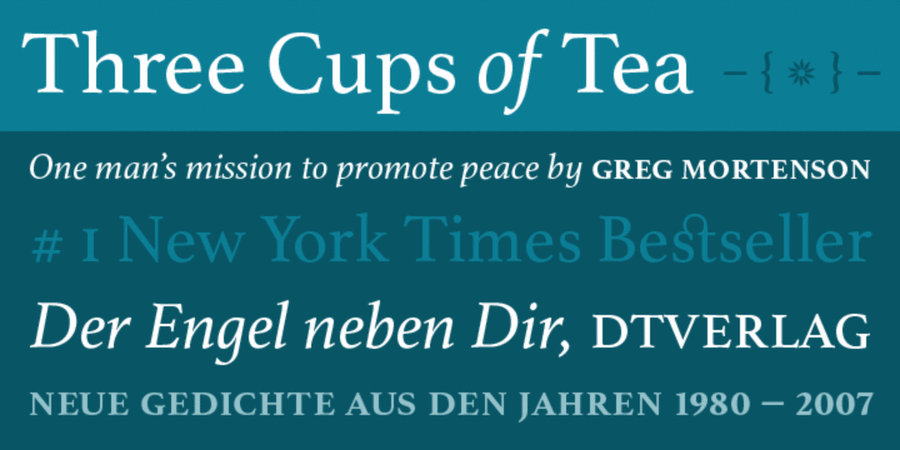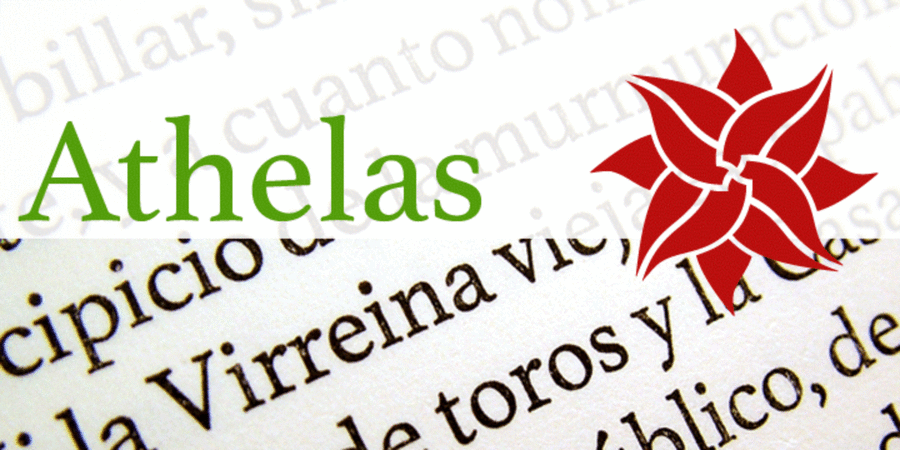
Це спроба повернутися до високого мистецтва друкарства, натхненна класиками британської літератури. Ателас нагороджений на шрифтовому конкурсі Granshan 2008. Цей шрифт в повній мірі використовує друкарську тишу, порожній простір на полях, між стовпцями, рядками, словами, формами літер і, нарешті, всередині самих символів. Він також призначений для використання переваг технічних досягнень офсетного друку. Ателас демонструє свої найкращі сторони в ретельно продуманих книжкових виданнях та хороших умовах друку. Гарніутра має великий набір символів, які охоплюють більшість мов, що використовують латинку, кирилицю та гречку. Хоча цей шрифт натхненний британською літературою, він поважає культурні цінності, що лежать в основі різних мов, де діакритичні знаки відіграють надзвичайно важливу роль. Ателас має чотири накреслення з понад 1000 символів в кожному, серяд них: капітель, лігатури, дроби, повний набір цифр для кожного типу використання та набір флеронів і стрілок.
Шрифт розробили Вероніка Буріан і Хосе Скагліоне в студії TypeTogether у 2008 році.